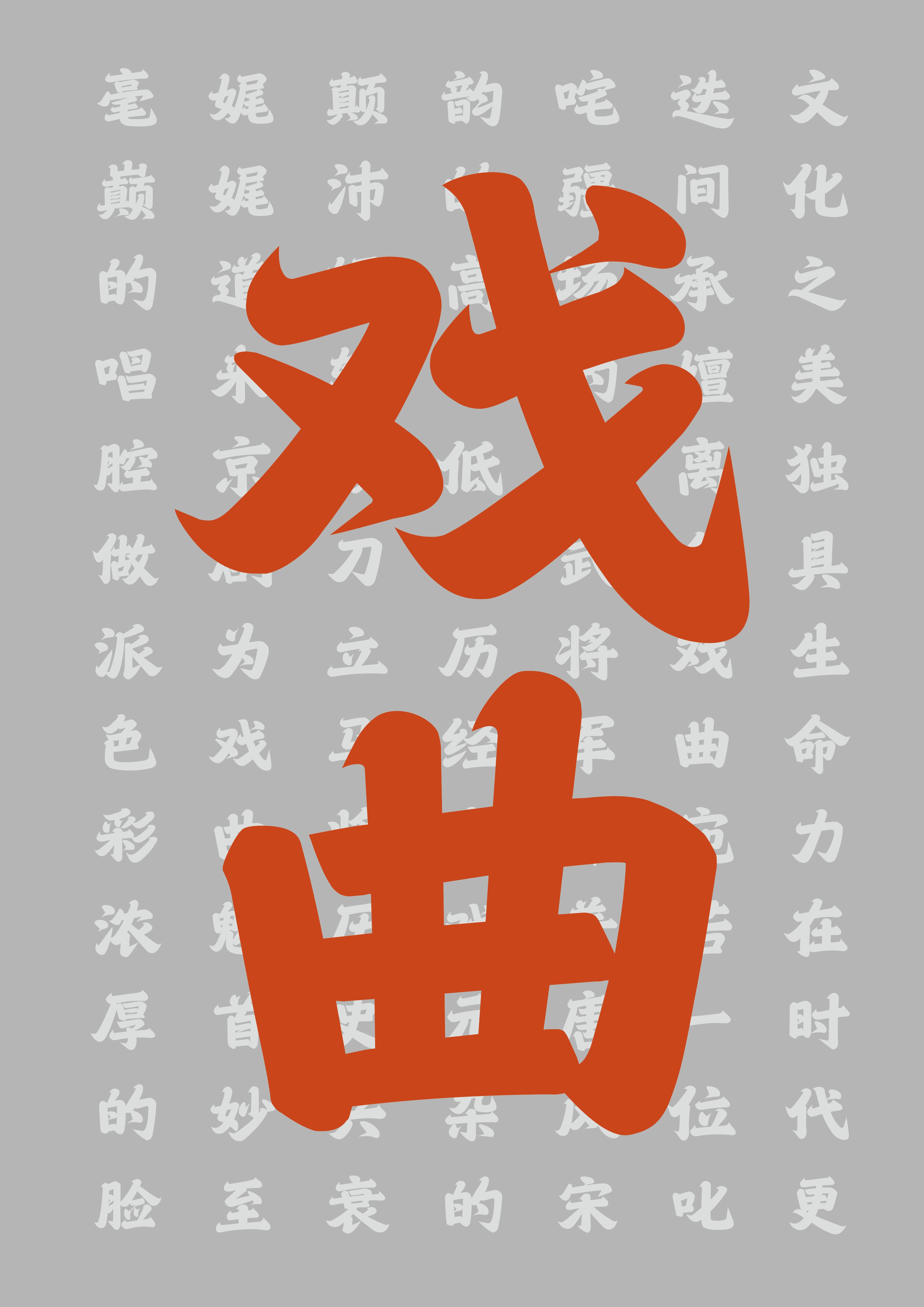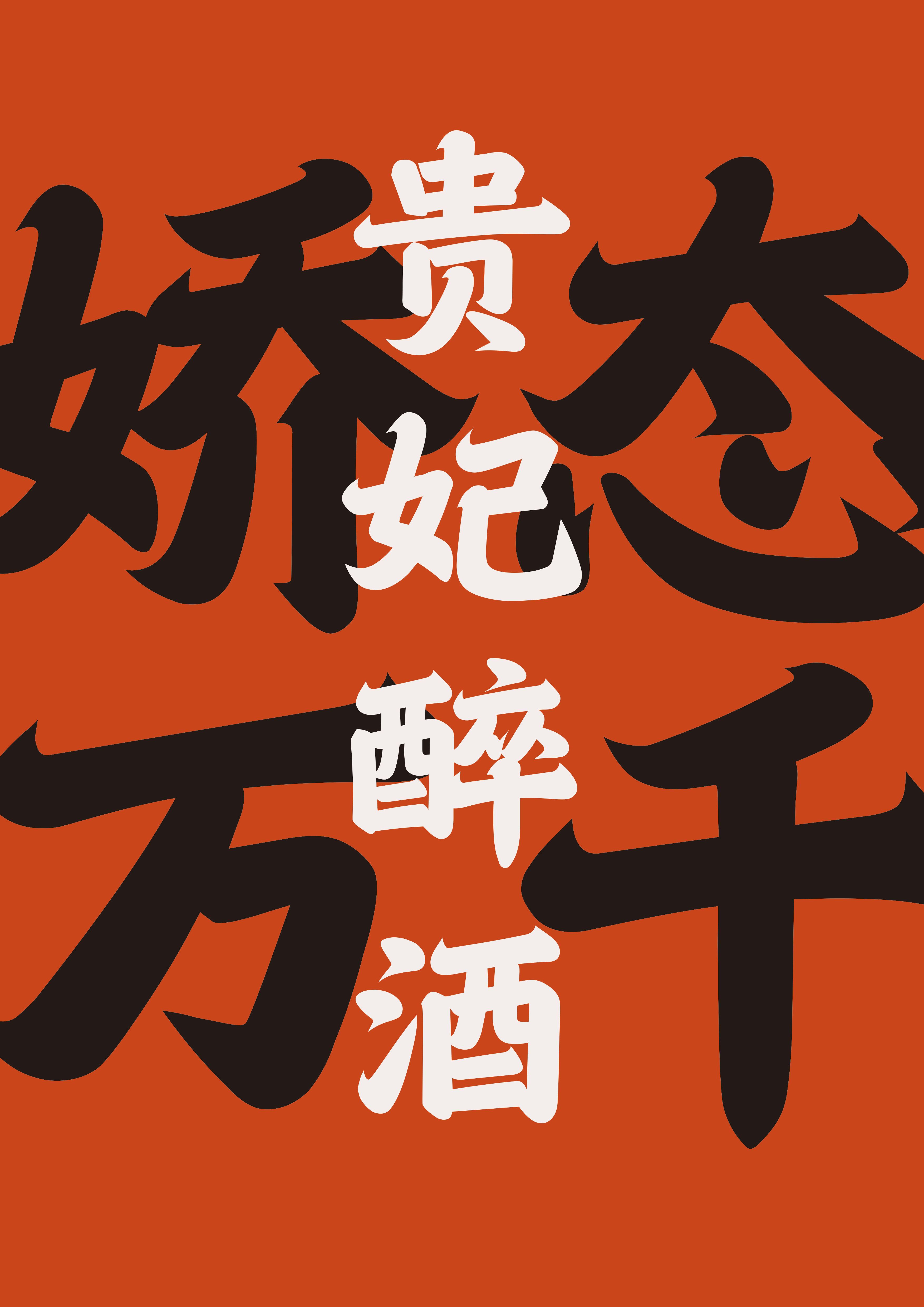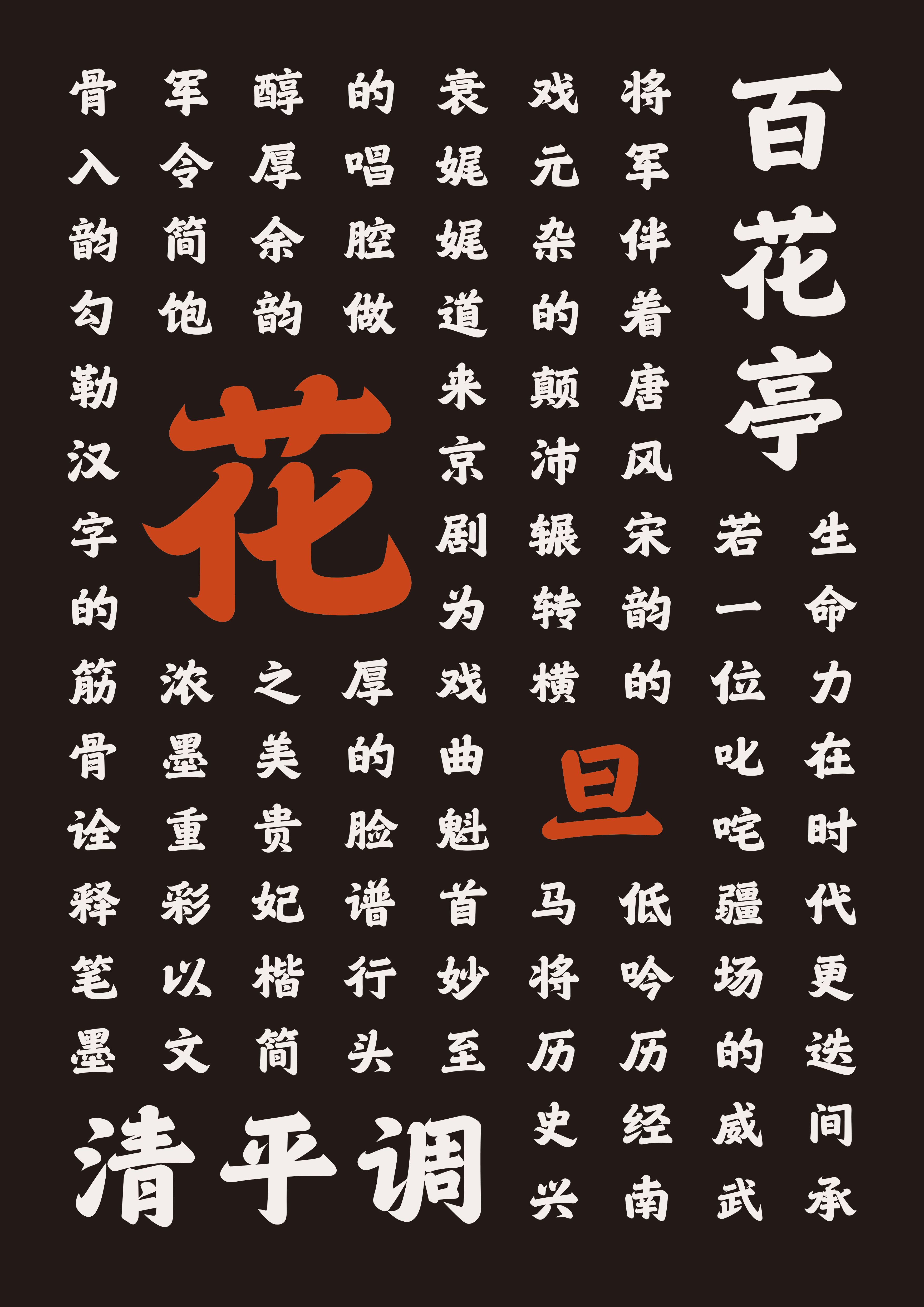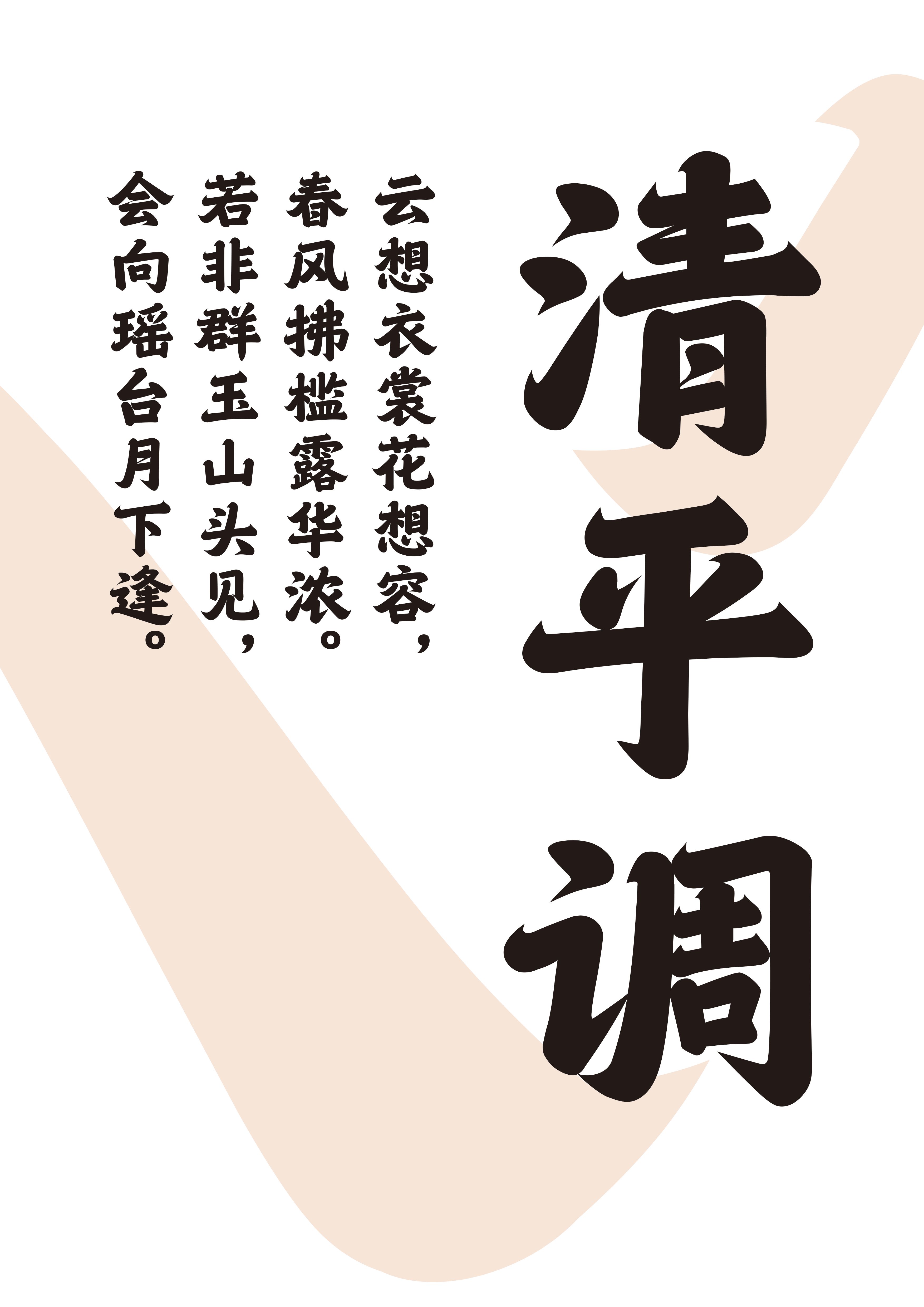
汉字之美贵妃楷获第八届「包豪斯奖」国际设计大赛铜奖!
汉字之美
汉字之美贵妃楷获第八届“包豪斯奖“国际设计大赛铜奖!
汉字之美贵妃楷简,撷取盛唐风姿,笔画丰腴,字形雍容贵气,极具视觉冲击力。行笔朗润流畅,收笔柔美上挑,朗畅有姿,呈现张弛有度的美感。笔画两端上挑的锋角,如同贵妃的凤钗,视觉呈现霸气又不失灵动之神韵。
汉字之美贵妃楷获第八届“包豪斯奖“国际设计大赛铜奖!
汉字之美贵妃楷简,撷取盛唐风姿,笔画丰腴,字形雍容贵气,极具视觉冲击力。行笔朗润流畅,收笔柔美上挑,朗畅有姿,呈现张弛有度的美感。笔画两端上挑的锋角,如同贵妃的凤钗,视觉呈现霸气又不失灵动之神韵。